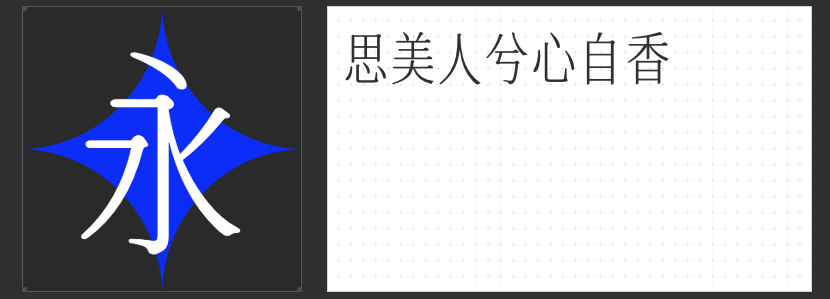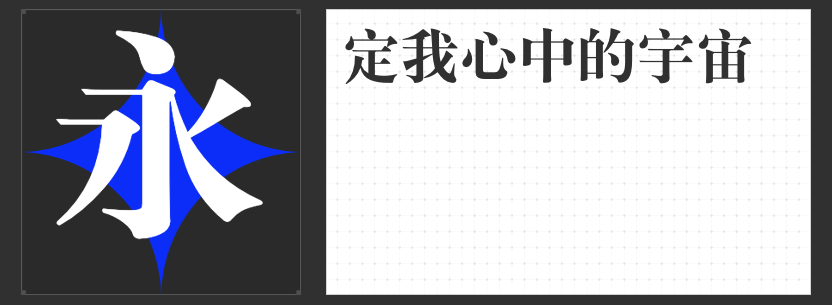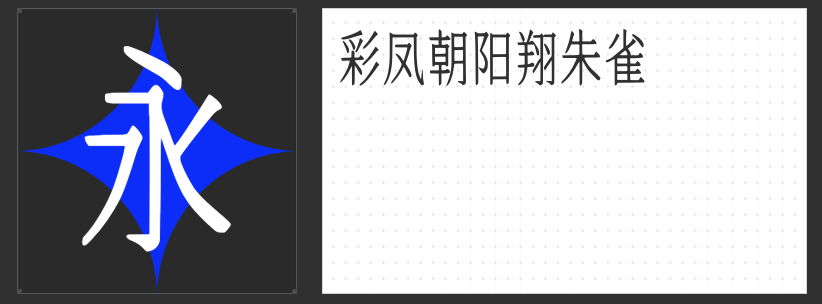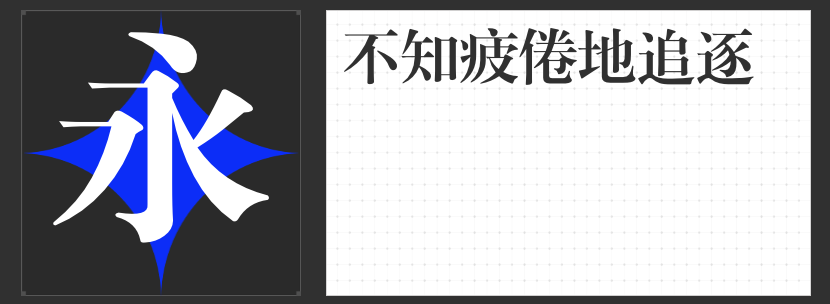
四款宋体佳作:重塑传统,演绎设计新美学
宋体作为汉字印刷的经典字体,以其横细竖粗的笔画对比、端庄严谨的结构和富有装饰性的衬线,成为东方美学的符号之一。随着设计语言的进化,当代宋体在传承中融入创新,既保留传统韵味,又拓展了视觉表达的可能性。以下四款宋体字库,以独特的设计语言诠释宋体的多元魅力,为设计师提供丰富的创意选择。
一、励字大标宋简繁
这款字体以老宋体为根基,融入黑体的力量感,形成横轻竖重、笔画粗细对比鲜明的视觉特征。其横线尾与竖线头呈三角状收笔,点、撇、捺等笔画尖端锐利,既保留传统宋体的装饰性,又通过简洁的线条强化现代感。字形端正清秀,结构严谨,既适合作为标题传递庄重感,亦能在长文本中保持阅读的流畅性。其简繁双版本设计,更满足了多元文化场景的需求。
二、字圈也字思美人宋体
以“思美人”为名,这款字体通过拉长笔画比例,赋予字形修长秀美的气质,宛如东方女性亭亭玉立。设计师在宋体架构中融入极精致的衬线,笔画转折处以圆润弧度过渡,弱化传统宋体的刚硬感,强化简约优雅的视觉韵律。其风格既适合文化、艺术类设计,传递含蓄内敛的东方美学,亦可作为时尚品牌的标题字体,展现刚柔并济的现代女性力量。
三、励字小标宋简
作为宋体字的标准范本,这款字体以严谨的笔法重构传统:横细竖粗的对比清晰,结构均匀饱满,衬线装饰简洁而不失雅致。其字形端正清秀,既保留了宋体在印刷文本中的易读性优势,又通过适度的笔画收放提升视觉层次感。无论是作为正文标题的点睛之笔,还是独立成篇的短文本排版,均能以克制的美学语言传递专业与信赖感。
四、机甲宋朱雀号
突破宋体的传统框架,这款字体以“机甲”为灵感,将硬核科技元素注入柔美宋体魂。笔画设计融合书法笔意与机械结构,横竖粗细对比中暗藏几何切割的锐利感,衬线部分以金属质感的棱角收尾,形成视觉冲击力。其修长字形与未来感细节,既适合游戏、科幻类标题设计,亦可作为品牌标识中的记忆点,诠释“柔中带刚”的东方哲学与科技美学。
这四款宋体字库以多元视角重构传统,为设计注入文化深度与视觉张力。无论是追求典雅、柔美、严谨还是前卫,设计师皆可从中找到契合项目气质的字体语言,让宋体在当代设计中焕发新生。